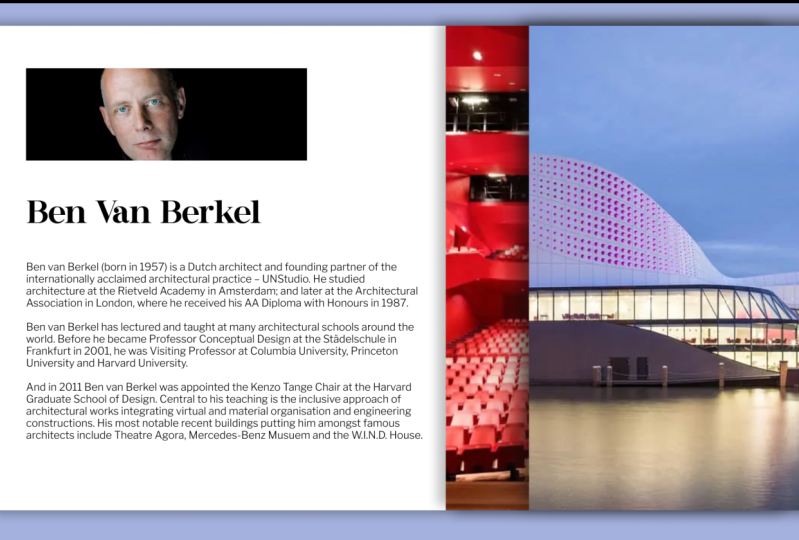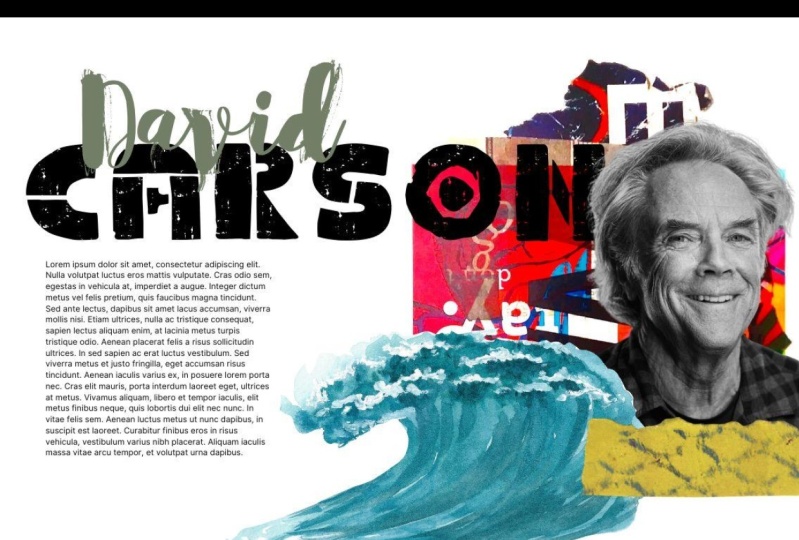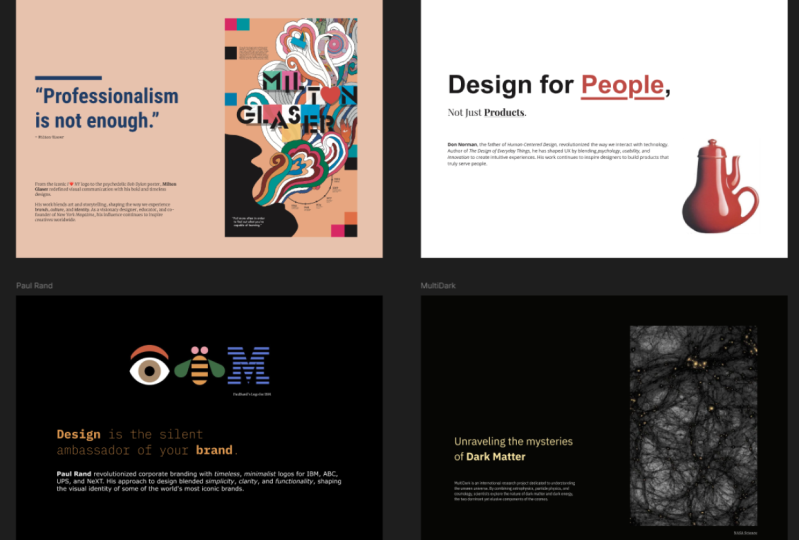
1. Einführung: Diese Woche werden
wir
Schriften für ein UI-Design auswählen . Wir werden damit beginnen
, darüber zu sprechen, was eine gute
Typografie-Kombination
ausmacht. Was macht einen guten
Körpertext aus und was macht einen guten Anzeigetext aus und
muss ihn miteinander koppeln. Und dann
wird das Projekt, an dem Sie diese Woche arbeiten
werden , darin bestehen, einen Künstler auszuwählen
, der Ihnen Spaß macht. Denken Sie darüber nach
, welche Eigenschaften der Künstler hat, und finden Sie dann Display
- und Körpertexte, die dem Kunststil
entsprechen gut
miteinander verbinden. Typografie macht
fast alles aus, was wir im Internet sehen,
und die Fähigkeiten, die wir
diese Woche gelernt haben , werden uns helfen,
die besten Schriften
für unsere UI-Designs auszuwählen . Lasst uns anfangen.
2. INSPIRATION: Bevor wir jetzt mit der Auswahl von Schriften
beginnen können, müssen
wir unser
Gehirn mit Inspiration füllen. Wir müssen uns Entwürfe aus
allen verschiedenen Branchen ansehen und ein Gefühl dafür
bekommen, was da draußen ist. Welche verschiedenen
Schriften lassen uns das Gefühl geben. Wirklich, wir sollten ziemlich viel
Zeit und wahrscheinlich
ziemlich regelmäßig
damit verbringen Zeit und wahrscheinlich
ziemlich regelmäßig andere Designarbeiten
anzuschauen und darüber nachzudenken, was
sie kommuniziert, darüber nachzudenken, was
sie kommuniziert,
was es uns sagt und
wie wir uns darüber fühlen. Es gibt uns auch Vorstellungen darüber,
wie wir die Schrift verwenden können. Wie Pablo Picasso bekanntermaßen sagte, kopieren
gute Künstler,
große Künstler stehlen. Jetzt wollen wir nicht
unbedingt Arbeit der Menschen
direkt stehlen, aber wir möchten
uns
von guten Dingen inspirieren lassen , die wir in
der Designbranche
gesehen haben . Jetzt befürworte ich mich immer dafür, Arten von Design abzuwenden, nicht Webdesign, nicht App-Design, sondern das Design als Ganzes zu betrachten ,
damit wir eine
viel breitere Palette von
Inspirationen haben und möglicherweise etwas
schaffen
etwas einzigartiger oder wussten, dass andere Designer in
der Branche es nicht tun. Wir könnten auf eine Website
wie Design-Inspiration kommen. Es gibt offensichtlich viele
Design-Inspirationswebsites, aber wir könnten dazu kommen, Inspiration zu
entwerfen und nach Typografie zu suchen. Und wir werden ziemlich
viele handgeschriebene Schriftzüge sehen, wenn ich ehrlich oder ziemlich funky kleine Illustrationen
mit Buchstaben bin. Aber all diese Briefe
werden uns ein Gefühl vermitteln. Sie werden
uns das Gefühl geben, dass sie zu etwas gehören. Dieser Buchstabe hier oder diese Nummer. Es sieht sehr königlich aus, es sieht sehr wichtig aus. Es sieht wertvoll aus. Und es sieht etwas zart aus. Und ich denke, es liegt an
den enormen Kontrasten zwischen den großen dicken Flächen
und den sehr dünnen Linien. Und möglicherweise weil es nur ein paar leicht
gerade Bereiche gibt, sieht
es aus und wenn
wir nach
etwas suchen , das
diese Eigenschaften kommuniziert, haben wir
vielleicht dafür gearbeitet Eine ziemlich hochwertige
Marke oder Schmuckmarke, zum Beispiel, dann können
wir nach
einer Schrift suchen ,
die diese Eigenschaften aufweist, aber viel
einfacher und klarer
und einfacher zu lesen ist , wenn wir
eine Schriftart wählen. Jetzt könnte man sagen, nun, das ist alles gut und gut. Ich erstelle eine App für eine Bank. Warum sollte ich also
irgendetwas mit solchen
Eigenschaften wollen ? Nun, eigentlich, ich,
Bank, wird
immer noch viele sehr
spezifische Eigenschaften haben. Und ich habe diese Briefe
hier aus einem
Fußballspiel ausgewählt , so wie es aussieht. Es sieht sehr sicher aus, sehr sicher, sehr vertrauensvoll und würde jeden Fall auf
einer Bank-Website funktionieren. Und dann
lautet meine Frage, warum ist das so? Liegt es daran, dass es
sehr dicke Buchstaben oder weil die Buchstaben
keinen Kontrast haben? Hat es mit der
Verfolgung dieser ziemlich
viel Abstand zwischen jedem Buchstaben zu tun. Hat es überhaupt
mit der Ausrichtung zu tun, wie dies zentriert ist und der Text ganz
zentral ausgerichtet ist. Es gibt viele typografische
Entscheidungen, die in
dieses sehr einfache Poster eingeflossen sind,
die es halb flach und
vertrauenswürdig machen , das für einen
Bankantrag funktionieren würde. Versuchen wir
darüber nachzudenken, was jetzt ist, damit
wir, wenn wir unsere Schriften auswählen, einige Vorstellungen davon haben,
wonach wir suchen. Jetzt könnte ich immer noch
Design-Inspiration und nächstes verwenden und einfach nach
Web-Typografie suchen. Also bekomme ich Dinge, die etwas
spezifischer
sind , und
Sie werden sehen einige Ideen für tatsächliche
und Detail wie möglich. Und wenn ich auf einer
Seite neben diesem Bild liege, konnte
ich nicht sagen, dass ich mit dieser Entscheidung
ziemlich zufrieden bin . Ich habe das Gefühl, dass dies eine ähnliche
Art von Botschaft
kommuniziert. Dann habe ich endlich eine
sehr schnelle einfache Seite für
Frank Gehry erstellt und hier eines
seiner architektonischen
Gebäude angelegt . Er ist ein Architekt ähnlich wie Dieter Rams ist sehr modernistisch. Ich habe mich für Sans Serifs entschieden, aber er hat einen anderen